Di artikel ini, Computer 1001 menyajikan 31 font untuk kartu ucapan Lebaran dan Ramadhan gaya Arab yang gratis dari Dafont dan Fontspace.
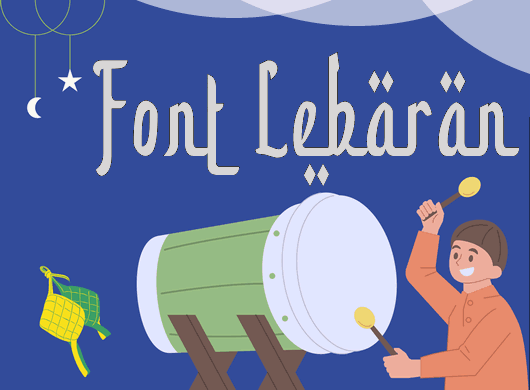
Font Idul Fitri- Font Ramadhan Gratis
Awal Ramadhan Font
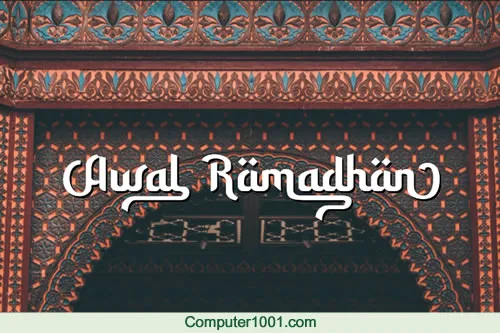
Font Awal Ramadhan adalah font latin mirip tulisan Arab yang cocok untuk desain tema formal.
Font Buka Puasa Bersama
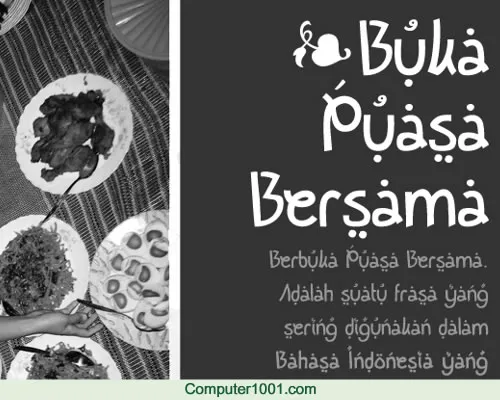
Font tulisan latin gaya Arab yang mirip tulisan tangan.
Ketupat Font
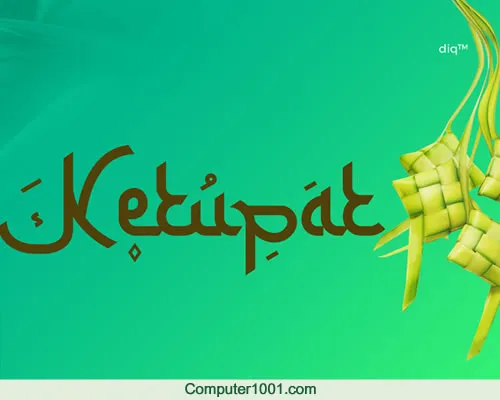
Font Ketupat Ramadhan
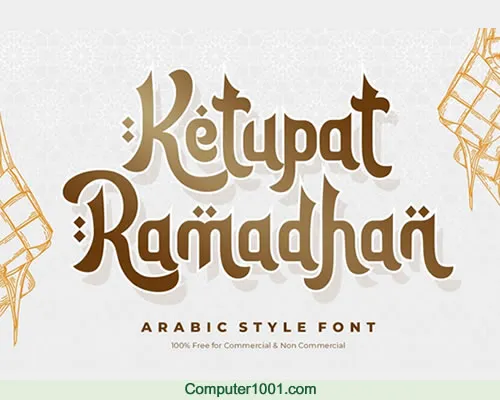
Font tebal yang cocok untuk banner Ramadhan atau Lebaran.
Memiliki 165 karakter (huruf besar dan kecil, huruf tanda aksen, angka, serta tanda baca).
Selamat Ramadhan Font
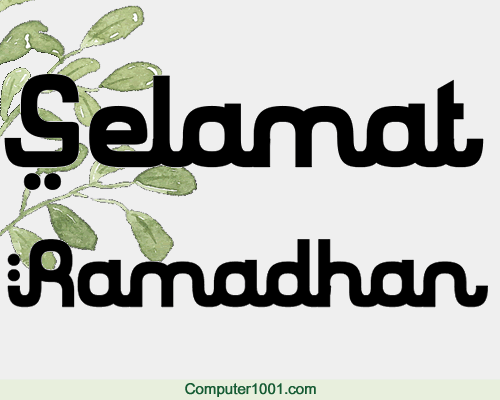
Font huruf Arab latin tebal. Coock untuk judul atau headline.
Bulan Rajab Font
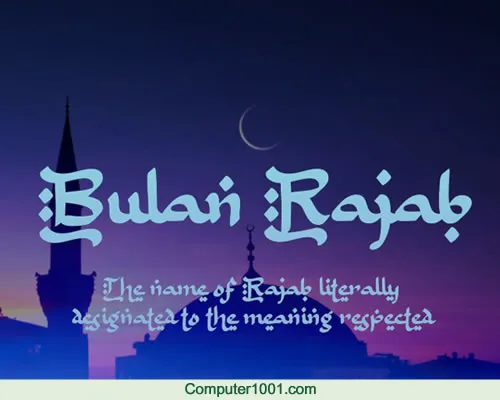
Font Bulan Rajab memiliki 95 karakter, dengan huruf kecil a-z dan huruf besar A-Z gaya Arab.
A Ahlan Wasahlan Font
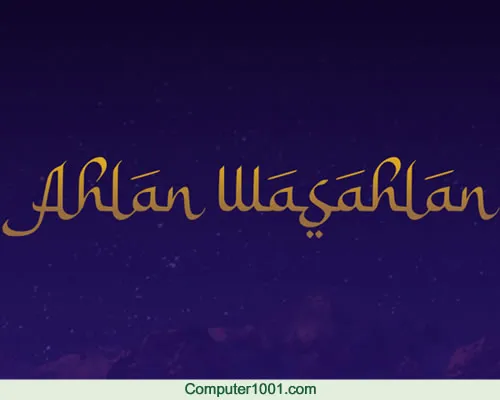
Dalam bahasa Arab, ahlan wa sahlan secara umum berarti ‘selamat datang’.
Font Syawal Khidmat
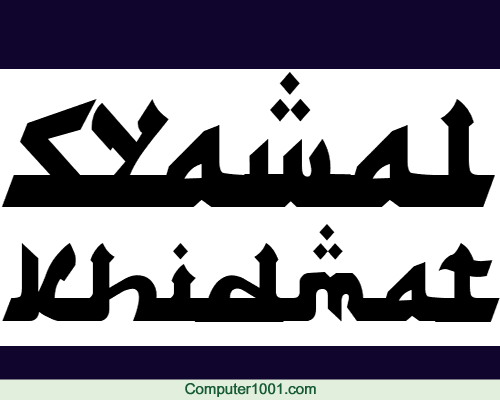
Font Arab latin tebal yang semuanya huruf kecil.
Font ini juga memiliki angka 0-9, tanda kurung, tanda seru, tanda sambung, dan tanda tanya.
Shaumy Font Arab Latin
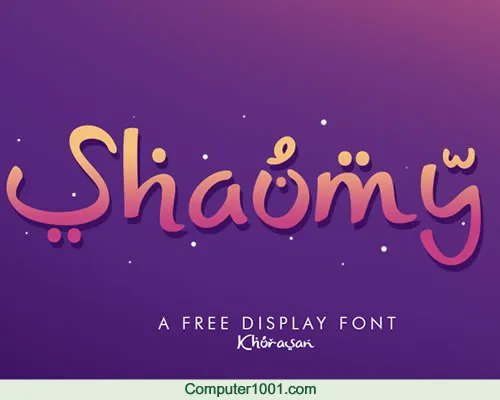
Font latin bentuk Arab yang keren.
Eid Fitri Font
Font ucapan Idul Fitri yang cantik.
Ketik tanda garis bawah _ pada keyboard untuk membuat gambar untaian ketupat.
Font Berlebaran Online
Font gaya kaligrafi Arab yang indah.
Lengkap dengan huruf besar dan kecil, angka 0-9, tanda baca, operator matematika, dan tanda kurung.
Ketik tanda garis bawah _ pada keyboard untuk membuat garis panjang melengkung.
Selamet Lebaran Font
Font gaya Arab yang semuanya huruf kecil. Juga ada angka dan beberapa simbol lainnya.
Ceria Lebaran Font
Selain memiliki huruf dan angka, font Ceria Lebaran juga ada tanda & # @ serta tanda kurung dan operator matematika (* + – /).
Aidilfitri Font
Font gaya Arab dengan bentuk tinggi kurus.
Maaf Lahir Batin Font
Tafakur Font
Satu lagi font gaya kufi.
Siti Maesaroh Font
Font latin bentuk Arab yang cantik.
Milhamsam Dzulhijjah Font Gaya Arab